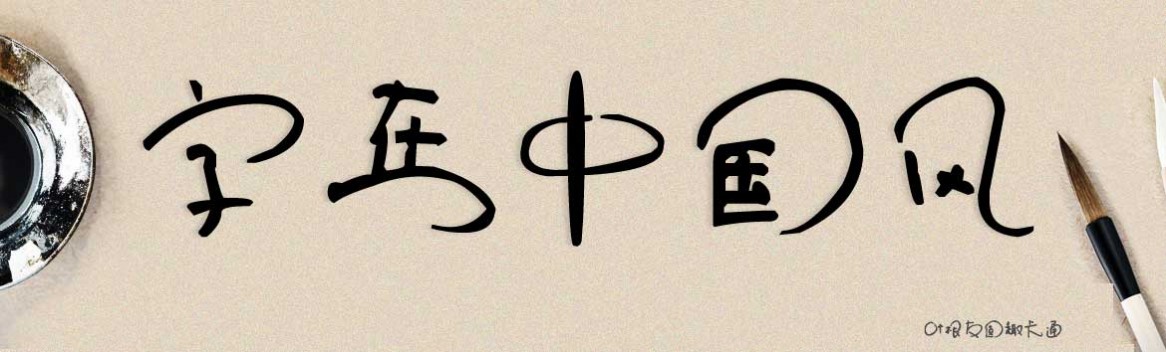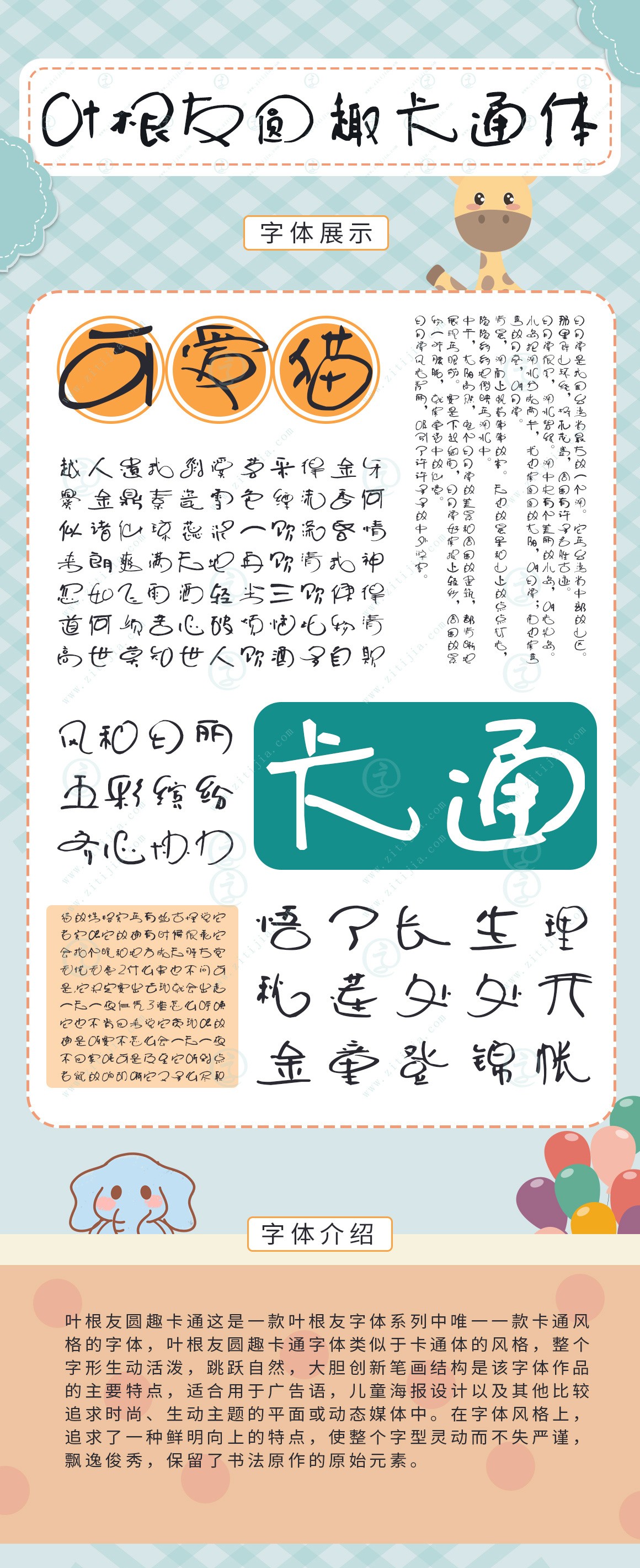
葉根友圓趣卡通體
字體作者:葉根友
創(chuàng)作年代:2010年5月
字體字數(shù):6763個中文漢字以及其他英文字母和阿拉伯數(shù)字
字體介紹
葉根友圓趣卡通體這是一款葉根友字體系列中唯一一款卡通風格的字體,葉根友圓趣卡通字體類似于卡通體的風格,整個字形生動活潑,跳躍自然,大膽創(chuàng)新筆畫結(jié)構(gòu)是該字體作品的主要特點,適合用于廣告語,兒童海報設(shè)計以及其他比較追求時尚、生動主題的平面或動態(tài)媒體中。在字體風格上,追求了一種鮮明向上的特點,使整個字型靈動而不失嚴謹,飄逸俊秀,保留了書法原作的原始元素。
風格展示